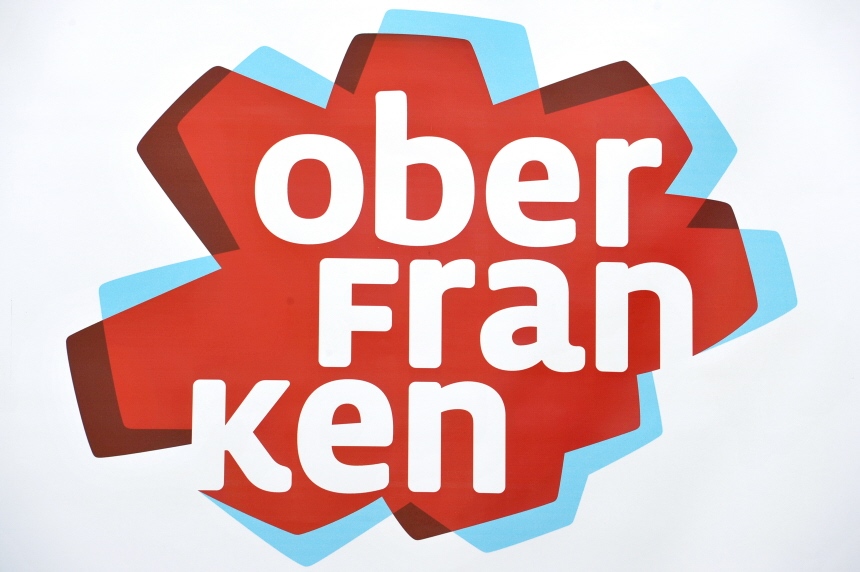
Die armen Oberfranken … der Versuch eines Logos.
Das Ding knallt, wirkt modern und freundlich. Besser als das alte angestaubte Logo in Business-Blau ist es locker. In letzter Zeit wurden etliche solcher Tourismus-Logos vorgestellt und dieses hier ist das einzige was ich auf den ersten Blick spannend finde.
es hat nur nix mit Oberfranken zu tun.
Naja, die bildhaften Stadt- und Regionallogos, die immer alle Sehenswürdigkeiten unterbringen wollen, kommen ja auch selten gut weg. Im Kontext mit den Drucksachen funktioniert das doch eigentlich ganz gut. *
Ich frage mich nur, ob nun wirklich auch jeder Verwaltungsbezirk eine Dachmarke braucht? :?
Ich hab schon Schwierigkeiten, mich mit meinem Bundesland zu identifizieren. Was soll das also bringen?
* Wobei ich mit der Bindestrich-Macke der Grafikdesigner nie anfreunden werde
Ich kenne Oberfranken nicht als bunt, laut, spritzig, modern, innovativ oder was uns das Logo sonst noch sagen soll. Oberfranken hat ganz andere Werte, und die sollten doch in einem Logo für eine Region transportiert werden.
Ingolstadt hat das wesentlich besser gelöst … ok, ist keine Region, aber ein guter Ansatz.
Hat jemand verstanden, was diese Dachmarke repräsentieren soll?
Wirtschaftsstandort? Tourismus? Politik? ...?
"Die Region" in ihrer Abstraktion/Allgemeinheit (egal welche) mit einem grafischen Symbol zu vereinen und dann auch noch positiv rüberzubringen halte ich ja inzwischen für eine fast unlösbare Aufgabe. Diese Vielfalt von Themenbereichen runterzubrechen auf eine geographische Gegebenheit, die oft auch noch recht willkürlich enstanden ist, ist schon inhaltlich-konzeptionell schwierig, und grafisch kaum eindeutig bewältigbar – am ehesten noch in einem Logo/Wortmarken-System, das die verschiedenen Bereiche gesondert repräsentiert.
Am Vorher-Nacher-Beispiel sieht man ja schon: das alte ist stilistisch Wirschaft/Industrie, das neue jetzt Tourismus/Politik. Und beide tun sich in der Formgebung schwer, etwas Repräsentatives, Regionsspezifisches zu finden, das vielleicht sogar noch ein außenstehender versteht (beim neuen Stuttgart-Sternchen-Logo soll ja irgendeine Stadtform als Grundlage dienen – ich sehe, obwohl ich von Zeit zu Zeit in Stuttgart bin, trotzdem nur einen Stern).
… zu simpel? Eher zu kompliziert. Fürcht fast, diese Sternform soll die Grenzen von Oberfranken beschreiben. Komplett blöd, das Wort "oberfranken" so dämlich zu zerstückeln. Ansonsten halt viel Beliebigkeit aufgeladen mit einem rasch vergänglichem, modischen Touch.
südtirol von meta ist super, eine ihrer letzten großen arbeiten ;)
wobei ich das oberfranken nicht schlecht finde, es gibt echt schlimmeres.
ich glaub das logo wird auch schon seit einigen monaten eingesetzt.
so als alleinstehendes logo siehts sicher etwas komisch aus, wobei die flächen
und farben viel platz für weitere kombinationen und einsatzmöglichkeiten geben.
Könnte mir vorstellen, dass der Logo-Ersteller am Abend zuvor im Kino einen 3D-Film gesehen und vergessen hat, die zweifarbige Brille abzunehmen..
Ansonsten finde ich die Zerstückelung des Textes auch nicht nachvollziehbar. Das musste frank & frei gesagt werden!
die form des hindergrunds (welcher eine sehr stilisierte form der region sein soll) bestimmt
ja die zerstücklung des textes, ich mach sowas auch gern und find es daher nicht so schlimm, anders trennen hätte man das wort auch kaum.
ober
frank
en
auch doof. alles in eine zeile schreiben wäre zu klein geworden.
von daher passt das schon. das logo ist sicher kein großer wurf, kann ja nicht jeder so ein schönes reduziertes logo besitzen wie wir (mal hatten).
wobei das logo unserer region auch nicht der hammer ist.
Ingolstadt hat das wesentlich besser gelöst … ok, ist keine Region, aber ein guter Ansatz.
was ist daran besser? ich find das schrecklicher, die form ist doch unmöglich.
und was sagt das logo aus?
kursiv = dynamik = autoindustrie?
stadt, land, plus = stadt, land, fluss?
raum für innovationen bietet der schriftzug (als logo würde ich das nicht beschreiben)
jedenfalls genug. das logo ist kein eyecatcher und bleibt bei weitem nicht so lange im
kopf hängen wie das oberfranken logo.
… und was sagt das logo aus? …
nichts. Der Ansatz gefällt mir aber besser: einfach und reduziert.
Wenn man das Wesentliche so gekünstelt in eine Form zwängen muß, dann taugt diese eben nicht als Hintergrund.
es geht natürlich auch immer schlimmer ... Vorarlberg (Politik) mit dem dynamischen Bogen:
Und hier noch unsere Tourismus-Logos:
Vorarlberg (Tourismus, aktuell, schön nichtssagend):
Ist es möglich, das alles, was eine Region ist, in einem Logo einigermaßen unterzubringen? Oder läuft es auf
- möglichst neutrale Wortmarken
- ein Modulsystem mit teils verschiedenen, teils gemeinsamen Aspekten
- abstrakte Formengebilde, die für gar nichts stehen
hinaus?
(Ich frage auch, weil ich grade für eine kleine, abgeschiedene Berggemeinde ein Erscheinungsbild gestalten darf - sozusagen eine "Mini-Region" für sich. Es wird Politik und Fremdenverkehr betrieben, Wirtschaft - zum Glück für mich - nicht ... und alles in sehr sehr kleinem Rahmen.)